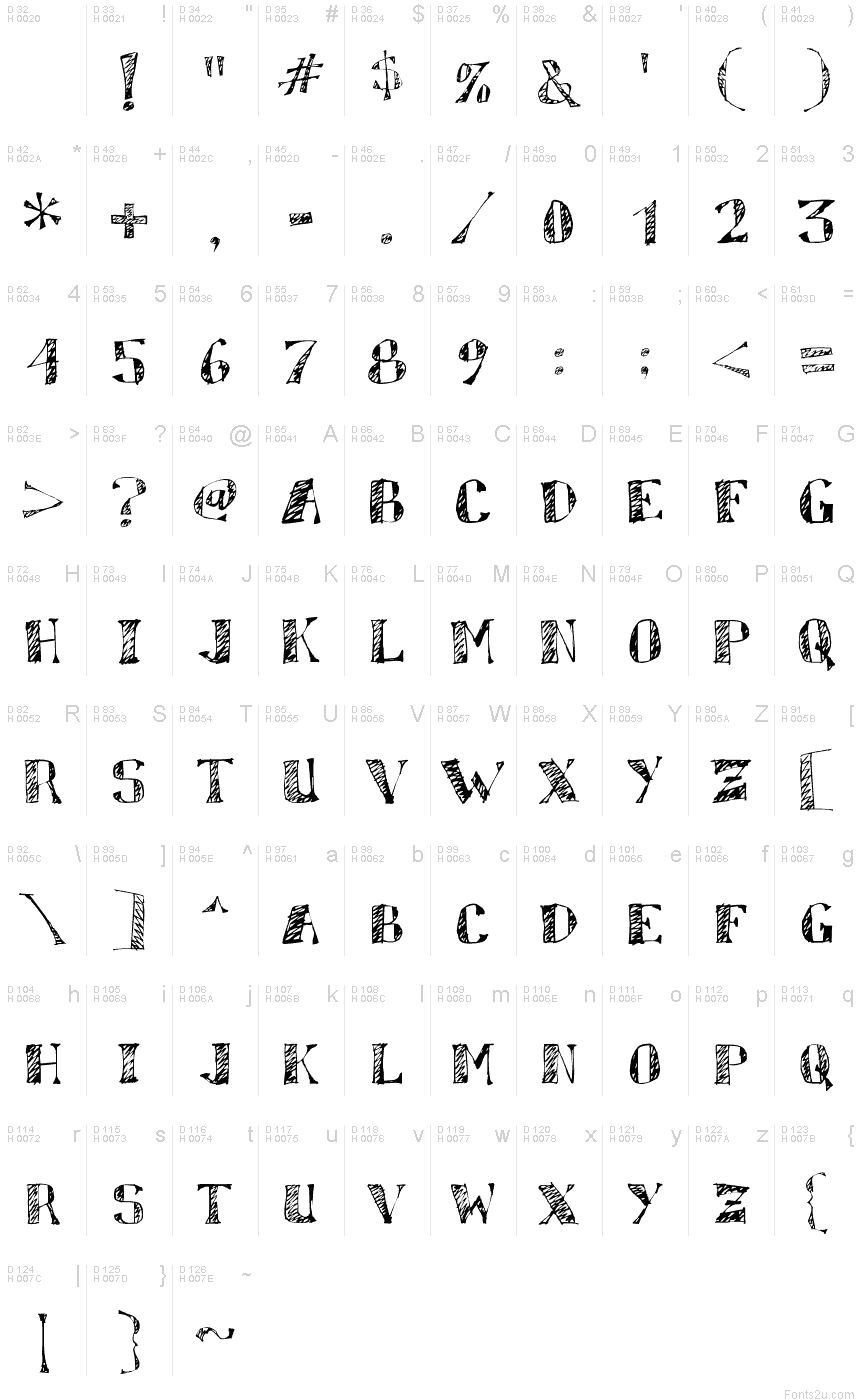
Sketchy to darmowy, szkicowy krój pisma z surowymi, odręcznie narysowanymi wielkimi literami, które wyglądają, jakby zostały przeniesione z projektu wykonanego markerem lub marginesu notatnika. Litery łączą w sobie wyrazistą, blokową wagę z postrzępionymi krawędziami, drapanymi kreskami oraz drobnymi skazami, dzięki czemu cały krój sprawia wrażenie niespokojnego i celowo niedokończonego.
To sprawia, że jest idealny do nagłówków plakatów, okładek zinów, ulotek zespołów, komiksowych plansz tytułowych oraz kreatywnego brandingu, gdzie font powinien być dynamiczny, głośny i sprawiać wrażenie wykonanego ręcznie. Użyj go, gdy chcesz, aby krótkie słowa, inicjały lub tytuły posiadały tę charakterystyczną, „nabazgraną” teksturę, nie wyglądając przy tym zbyt schludnie czy technicznie.